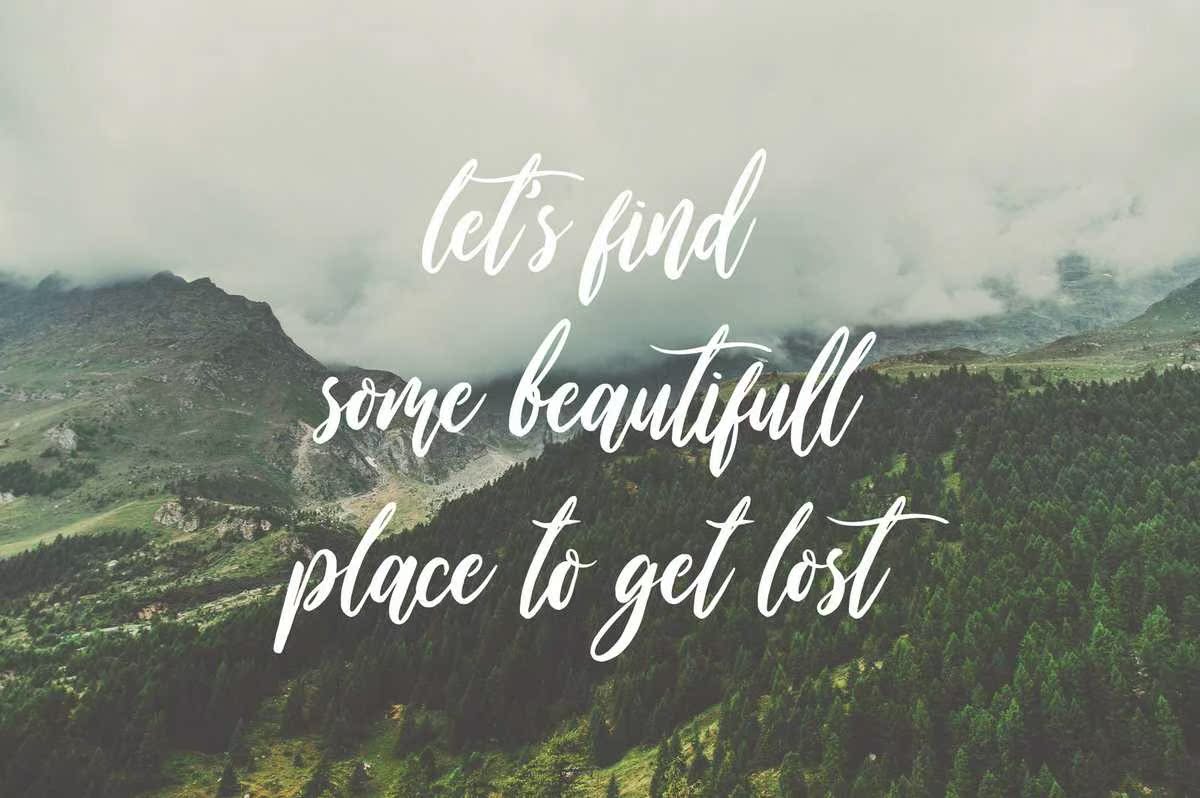
WildOnes是一款手工手绘脚本字体,灵感来自现代的多媒体风格。它在同一时间内既有趣、好玩又美丽。WildOnes使用一种字体风格、一些可选字符和ExtrasLeaveVector,soyoucancombineit’s all and Make any design you want,It's very fun.它非常有趣。适合并适用于制作字体设计、圣诞贺卡、品牌、徽标,产品包装、邀请函、qoutes、t恤、labelposteretc.WildOnes是一款手工手绘手写字体,灵感来自现代的拼图风格。它让您在同一时间体验到乐趣、玩乐和美丽。Wildone可以与OneFontStyle、某些可选字符和ExtrasLeaveVector结合,从而可以组合所有您想要的设计,它非常有趣。适合并适用于创建字体设计、圣诞卡、品牌、徽标、产品包装、邀请、qoutes、t恤、labelposteretc。